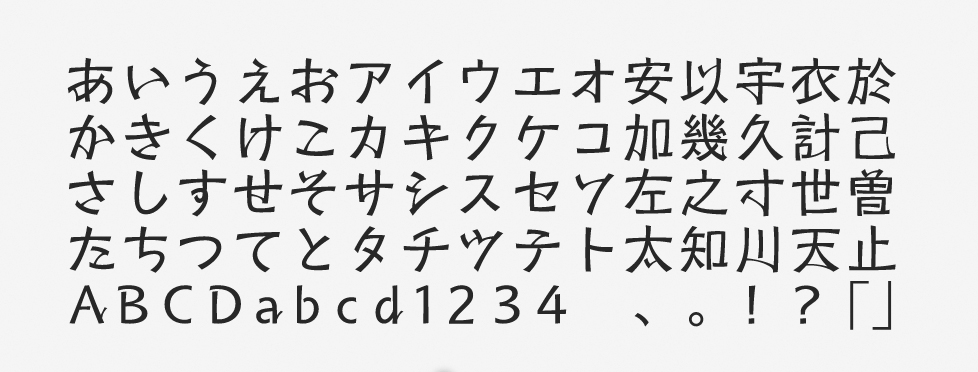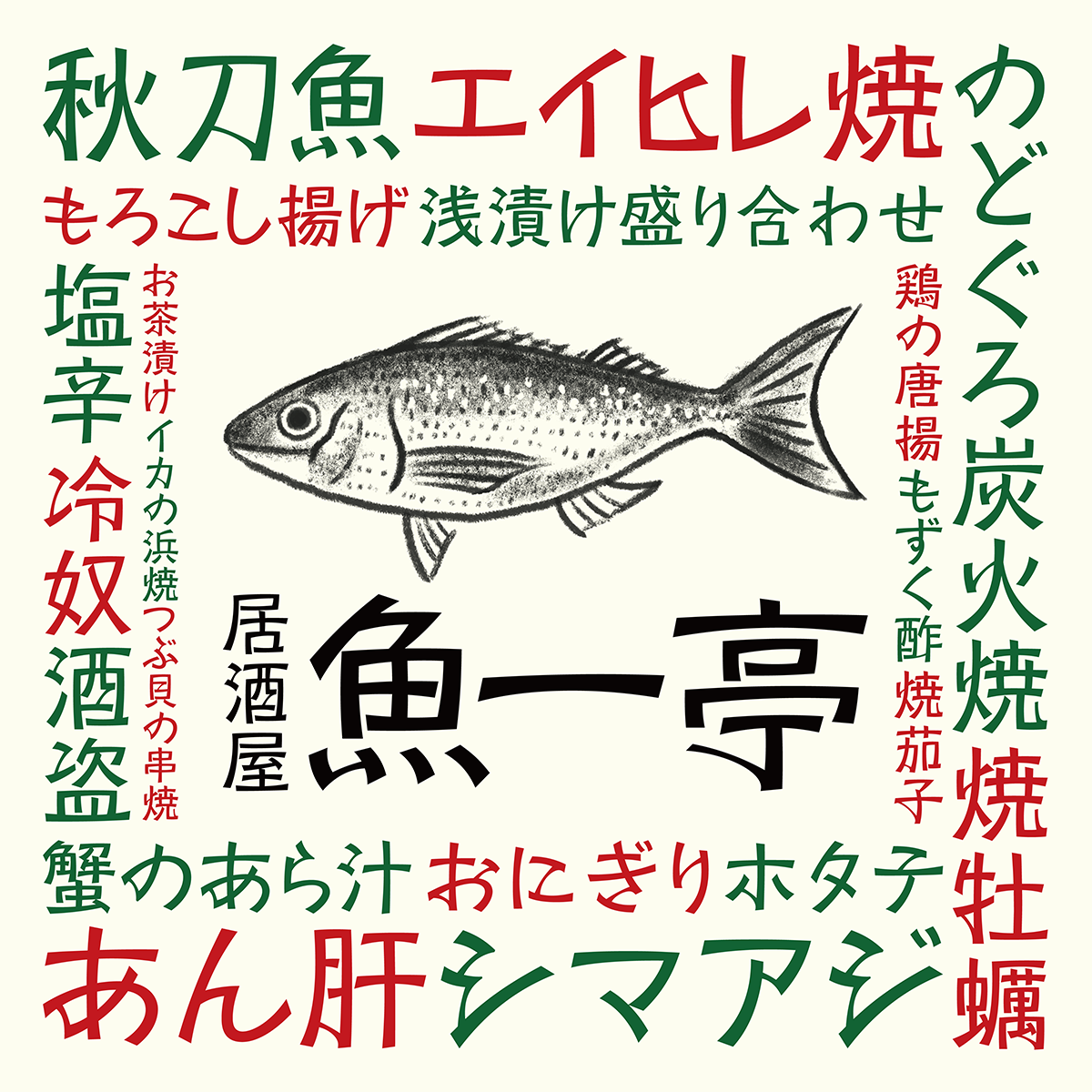
「くもやじ」について
くもやじは、モリサワ国際タイプフェイスコンテスト(モリサワタイプデザインコンペティションの前身のコンテスト)の入選作品から誕生しました。まるで蜘蛛の糸のような装飾が文字のさまざまな箇所に張り巡らされ、ユニークな印象に仕上げられています。2023年の秋には、和文・欧文ペアカーニングと最新のIVSに対応したAP版フォントとしてもリリースされました。
「くもやじ」の特徴
文字のパーツをつないだ細いラインによって、跳ねるような勢いも感じさせるフォントです。とにかく個性が強いため、デザインにおけるアクセントとして便利で、斬新な表現を目指せるでしょう。
大きなサイズの文字に最適で、タイトルやキャッチフレーズなどに使えばインパクトを出せます。それぞれの文字がグラフィックのような側面もあるため、写真やイラスト素材が少ない媒体で、タイポグラフィ中心のデザインに仕上げる場合にも便利です。
蜘蛛の糸のようなエレメントが個性的なフォントです。作例では文字組みで工夫し、縦組みと横組みを混在させつつも、色を変えて単語の区切りを見せながら楽しく仕上げました。写真などがなくても印象に残り、親しみも表現できるフォントです。
タイトル・見出し、書籍、雑誌、パンフレット、商品パッケージ、ロゴ、ラベル、チラシ、POP、看板、サイン、ディスプレイ広告、WEB、バナー